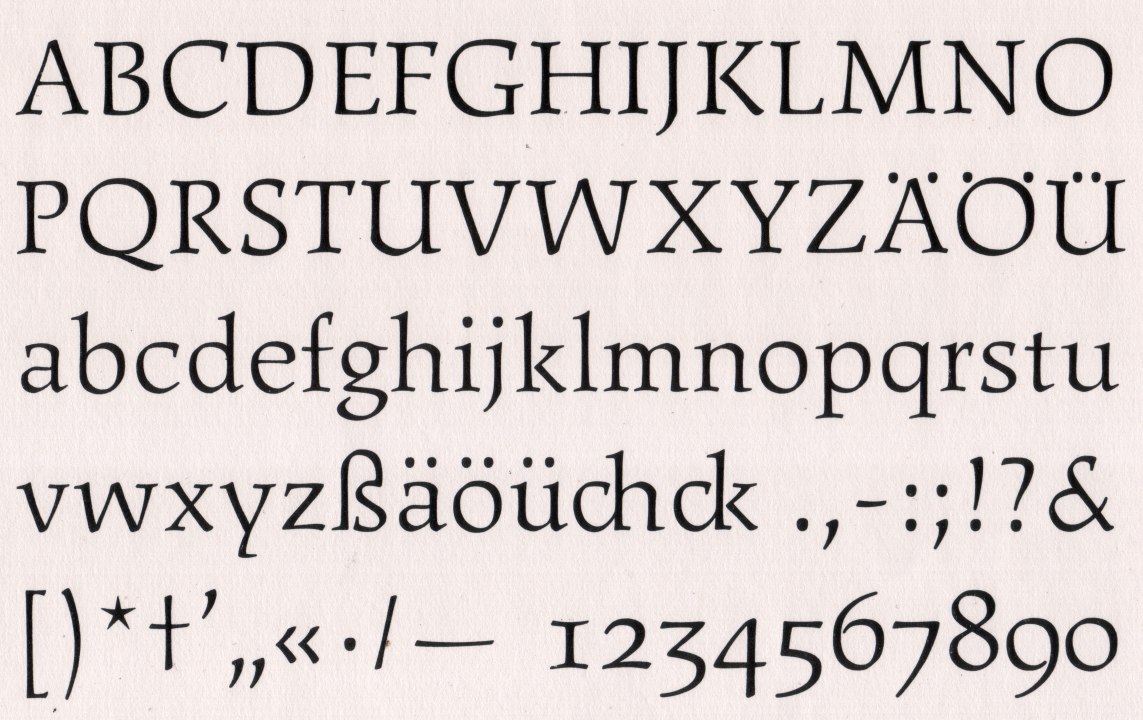
Антиква — это… Что такое Антиква?
Антиква (шрифт с засечками)Анти́ква (лат. antīqua «древняя») — класс типографских наборных шрифтов с засечками, появившийся в эпоху Возрождения в Западной Европе. Основой для разработчиков первых гуманистических, или ренессансных антикв служил рукописный книжный почерк — гуманистический минускул.
Николя ЖансонПо одной из исторических версий, первая антиква была вырезана гравером Николя Жансоном в Венеции в 1470 году. Однако похожие шрифты создавались и ранее[1]. В частности, в середине 1460-х неподалеку от Рима в монастыре Суабико свой вариант гуманистического шрифта создали типографы Свейнхейм и Паннарц. Как бы то ни было, первым поколением антиквенных шрифтов считается ренессансная венецианская антиква. Позже появилась французская, голландская и английская разновидности этого шрифта. Ренессансная, или гуманистическая антиква отличалась некоторой лапидарностью. Пришедшая ей на смену переходная антиква была утонченнее.
Антиква старого стиля
Репродукция шрифта Николя Жансона. Венеция, около 1470 года Пример итало-французской антиквы (шрифт Adobe Garamond)Ренессансная антиква
Ренессансные антиквы по внешним чертам и времени создания относятся к двум группам: венецианской и итало-французской.
Венецианская антиква появилась раньше, она ближе всего к прототипу — письму ширококонечным пером. Контраст между основными и вспомогательными штрихами небольшой, оси овальных элементов наклонены, засечки асимметричны, каплевидные элементы имеют форму следа от прямоугольного пера, перемычка в букве е наклонная.
Современные шрифты на основе венецианской антиквы Николя Жансона и Франческо Гриффо — Adobe Jenson, Nicolaus, Centaur.
Итало-французская антиква — более поздняя, XVI века; к этому времени изготовление шрифтов достигло большего совершенства, что позволило увеличить контраст между штрихами.
Перемычка в букве е стала горизонтальной, тоньше и более правильной формы стали засечки, капли стали более округлыми.
Сегодня представлена шрифтами Гарамон, Palatino, Bembo, Caslon и другими на основе работ Клода Гарамона, Альда Мануция и прочих авторов.
Переходная антиква
Пример переходной антиквы (шрифт Times New Roman)Переход от старинной антиквы начался в конце XVII века. Традиционно считается, что новый рисунок шрифта впервые создавался для нужд короля Франции Людовика XIV. Работа основывалась не на рукописном рисунке, а на геометрических построениях и «природных пропорциях».
В XVIII веке был создан шрифт Baskerville (назван по имени его создателя Джона Баскервиля).
Переходные антиквы отличаются более сильным контрастом, вертикальными осями овальных букв, скруглёнными симметричными засечками, полузакрытой формой знаков. На форму символов повлияло изобретение в XVII веке остроконечного пера (см. раздел Влияние каллиграфии на форму символов).![]()
Количество переходных антикв невелико, но применение они имеют самое широкое.
Новая антиква
Наиболее правильная и геометричная среди разных стилей антиквы. Для неё характерны высокий контраст, вертикальные оси овальных элементов, закрытые формы знаков, округлые каплевидные элементы. В удобочитаемости уступает старостильным и переходным антиквам.
За границей являлась основным шрифтом для набора текстов с конца XVIII до начала XX века; в СССР продолжала широко использоваться
Примеры новой антиквы — шрифты Bodoni, Didot, Обыкновенная новая[3], Computer Modern.
Связь рисунка шрифта и свойств бумаги
Металлические наборные шрифты эпох Ренессанса и барокко (антиква старого стиля и переходная антиква) создавались для печати на матовой бумаге, доступной в то время. Новая антиква использовалась для печати на глянцевой бумаге.
Для сохранения целостного впечатления от издания следует учитывать это, используя шрифты для печати на подходящей им бумаге
Связь рисунков шрифтов с национальными языками
В своей известной работе «Типографика» швейцарский типограф и графический дизайнер Эмиль Рудер обращает внимание на то, что шрифты могут быть связаны с языком их создателей: «Шрифт Гарамон связан с французским языком, Кезлон — с английским, а Бодони — с итальянским. Любой из этих трех шрифтов, употреблённый в наборе на другом языке, может понести ощутимый эстетический урон. Например, Бодони, примененный в немецком наборе,— уже не тот шрифт; картина иностранного текста, пестрящего прописными буквами, ему противопоказана»[5].
Влияние каллиграфии на форму символов
Письмо пером (ширококонечным и острым) повлияло на форму букв наборных шрифтов.
При письме ширококонечным пером толщина линии зависит от направления движения пера: движется ли перо вверх, вниз или в сторону, что хорошо видно в буквах М и Н.
При письме остроконечным пером, изобретенным в XVII веке, толщина штриха зависит уже от силы нажатия на перо, а не от направления его движения. Это, наряду с прогрессом в работе с металлом, повлияло на форму букв: они стали более контрастными и симметричными.